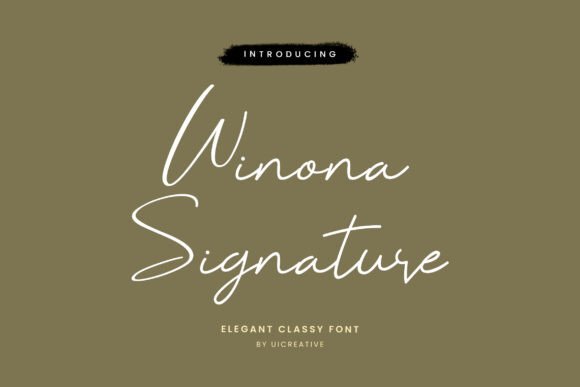
Winona Signature
Winona Signatureのような高品質の素材をお探しの場合、このプレミアムパッケージはクリエイティブなプロジェクトに素晴らしい選択です。
POD(オンデマンド印刷)製品、結婚式の招待状、またはソーシャルメディアのグラフィックを作成している場合でも、Winona Signatureは理想的です。